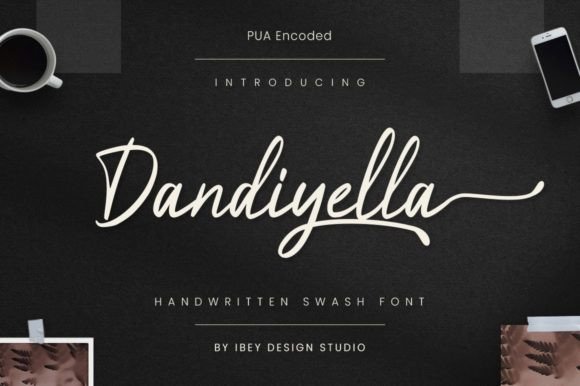
Dandiyella
Dandiyella – A Fonte Manuscrita que Faz Cada Palavra Dançar
Se você está em busca de uma tipografia que traga personalidade, leveza e um toque de diversão aos seus projetos, Dandiyella é a escolha perfeita. Essa fonte manuscrita combina caracteres encantadores e brincalhos que parecem “dançar” ao longo da linha de base, garantindo que seu design se destaque imediatamente.
Por que escolher Dandiyella?
- Estilo único e cativante: Cada glifo foi desenhado à mão, transmitindo uma sensação de proximidade e criatividade que poucas fontes conseguem oferecer.
- Versatilidade criativa: Ideal para convites, branding, capas de livros, posts de redes sociais e qualquer peça que precise de um toque de personalidade.
- PUA encoded: Dandiyella utiliza codificação Private Use Area (PUA), permitindo acesso fácil a todos os glifos e swashes – basta escolher o caractere desejado e ele aparecerá instantaneamente.
Como usar Dandiyella no seu próximo projeto
- Identidade visual: Use Dandiyella nos logotipos ou slogans para transmitir um ar artesanal e amigável.
- Materiais impressos: Convites de casamento, cartões de visita e flyers ganham vida com a fluidez dos caracteres.
- Conteúdo digital: Destaque citações, chamadas de ação e legendas nas redes sociais para aumentar o engajamento.
- Combinações tipográficas: Misture Dandiyella com fontes sans‑serif clean (como Montserrat ou Open Sans) para criar contrastes modernos e equilibrados.
Dandiyella não é apenas mais uma fonte manuscrita; é um convite para que suas ideias “ganhem vida” e dancem na tela ou no papel. Sua codificação PUA facilita o acesso a swashes e variações, tornando o fluxo de trabalho mais ágil. Experimente Dandiyella hoje mesmo e transforme projetos comuns em verdadeiras obras‑de‑arte!